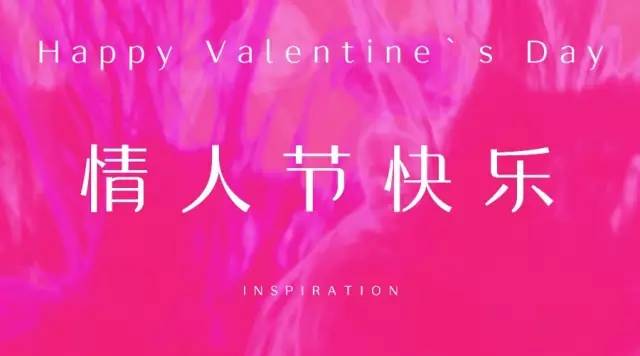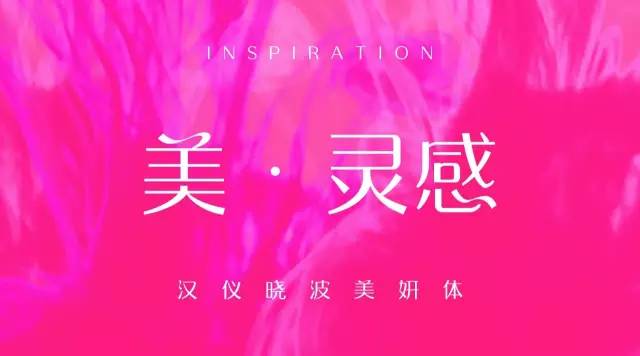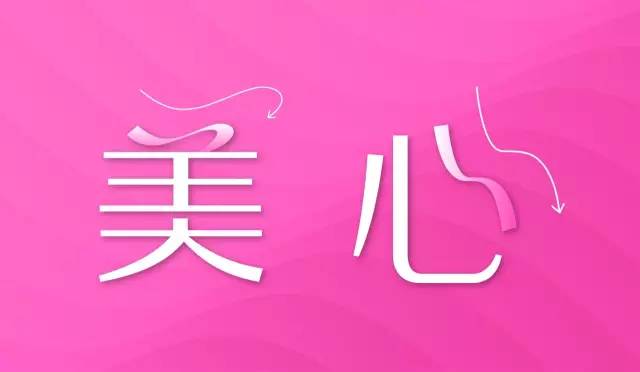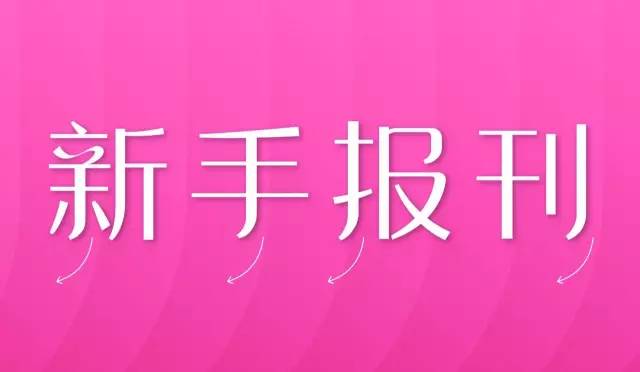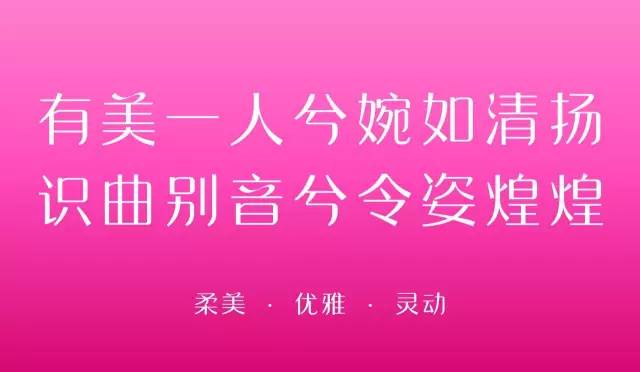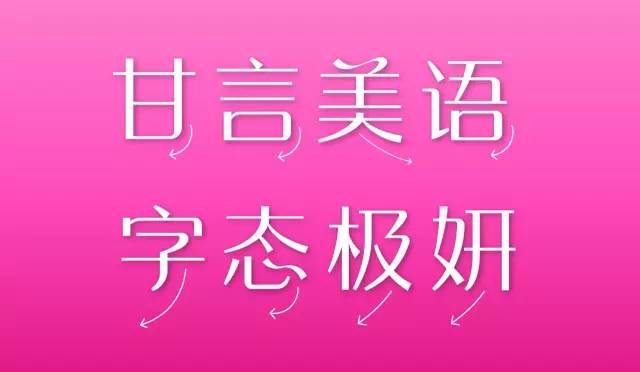
美丽、优雅、可爱、温柔的字体大全,情人节再也不用到处找字体了。
/ 汉仪晓波美妍体 /
是的,
我们又出新品了,
情人节大声写出来!
汉仪助你表白天下,
美丽、优雅、可爱、温柔… 还有超多女性字体,
情人节,等你来翻(xià)牌(zǎi)!
笔芯
专属节日×女性字体
翻翻日历,
即将邂逅的女性专属节日,
情人节、女生节、妇女节、母亲节…
浪漫温情,
其实,
字体和节日一样,
每款字体都有自己的专属特性,
小编精心挑选了19款女性字体,
(含新品预告哦!)
让你遇到的每个温情节日,
都有汉仪陪你一起度过!
汉仪秀英体 & 汉仪黛玉体
汉仪经典装饰女性字体
汉仪海纹体 & 汉仪清韵体
汉仪经典装饰女性字体
汉仪雅酷黑 & 汉仪铸字美心体 & 汉仪瑞意宋
汉仪新派标题女性字体
(新品预告:汉仪铸字美心体,敬请关注)
汉仪清雅体 & 汉仪典雅体
汉仪优雅正文女性字体
汉仪润圆 & 汉仪全唐诗
汉仪优雅正文女性字体
(汉仪润圆家族字体)
汉仪喵魂体 & 汉仪新蒂下午茶 & 汉仪尚巍清茶体
汉仪可爱休闲女性字体
新品预告:汉仪尚巍清茶体,敬请关注)
汉仪春然体
汉仪潇洒帅气女性字体
(新品预告:汉仪春然体,敬请关注)
汉仪许静行书 & 汉仪李政恩小楷 & 汉仪青云体
汉仪温婉手写女性字体
(新品预告:汉仪许静行书,敬请关注)
新品字体
汉仪晓波美妍体 ︳一款秀美妍丽的女性字体
设计师:胡晓波
字体风格:简约 / 现代 / 时尚 / 女性 / 柔软 / 休闲 / 轻松 / 平和
应用领域:标志 / 广告 / 游戏 / 动漫 / 影视 / 包装
节日属性:情人节 / 妇女节 / 母亲节 / 中秋节 / 七夕节等
字体特征
两点的连接处理增加了笔画的流动感,丝滑流畅
竖勾的笔势顺畅圆润
转折处进行了圆滑的处理,一笔带过
横向简约,纵向变化,使字体看起来灵动、优雅,
中宫较大,字面整齐,使字体看起来稳定、从容。
字体应用示例
这么多款性格的女性字体,
你翻了谁的牌呢?